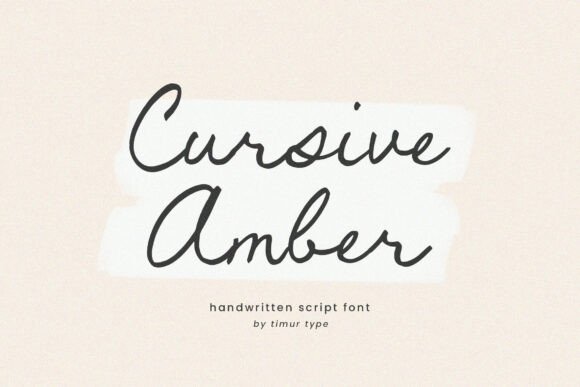
Cursive Amber
Encontrar os elementos de design certos pode ser um desafio, mas Cursive Amber oferece uma coleção excepcional que eleva o seu trabalho instantaneamente.
Quer você esteja criando produtos POD (Print on Demand), convites de casamento ou gráficos para mídias sociais, Cursive Amber é a escolha ideal.